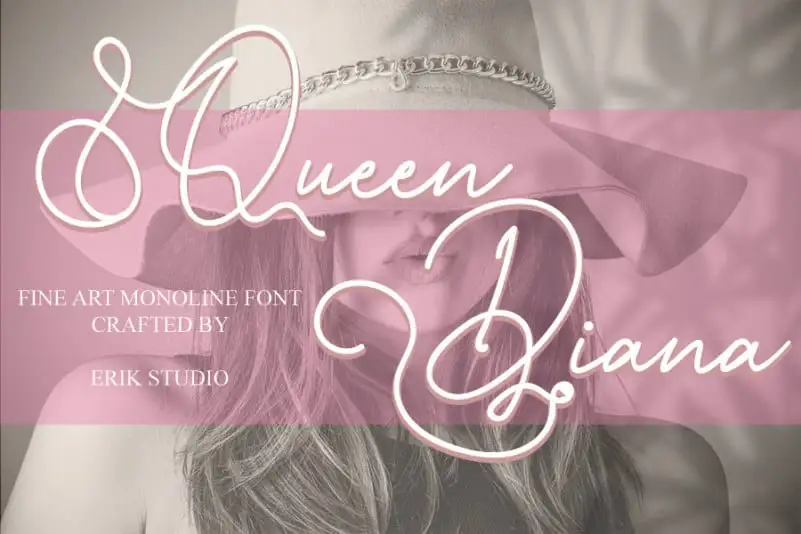
Queen Diana Script Font – Download Grátis
A Fonte Queen Diana Script é uma escolha perfeita para aqueles que buscam a harmonia entre delicadeza e elegância no seu design editorial ou artístico. Masterizada com cuidado, esta fonte escrita à mão se destaca pela sua sutileza e elegância, oferecendo um toque personalizado em qualquer projeto. Especialmente adequada para trabalhos que exigem uma escrita delicada, a Queen Diana Script pode transformar suas ideias criativas em realidade. Seja ela usada como título ou em subtítulos mais discretos, esta fonte proporciona um contraste encantador e um toque sofisticado ao texto impresso. Para designers que buscam uma solução versátil para seus trabalhos de design editorial, o Queen Diana Script é uma ótima escolha. Suas linhas suaves e suas nuances elegantes garantem um estilo impecável em qualquer uso – seja em anúncios publicitários, cartões de visita ou até mesmo em sites e blogs digitais.